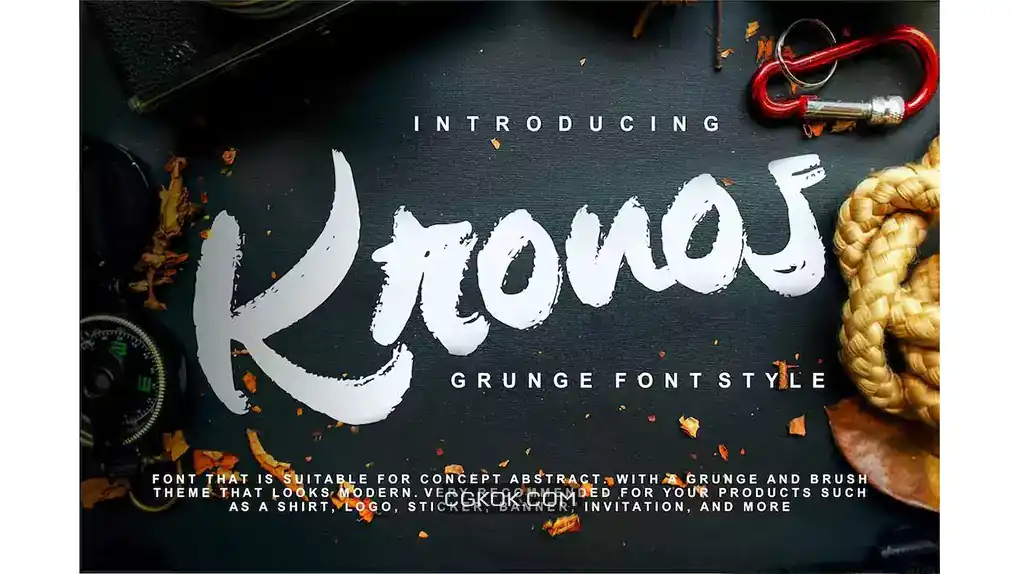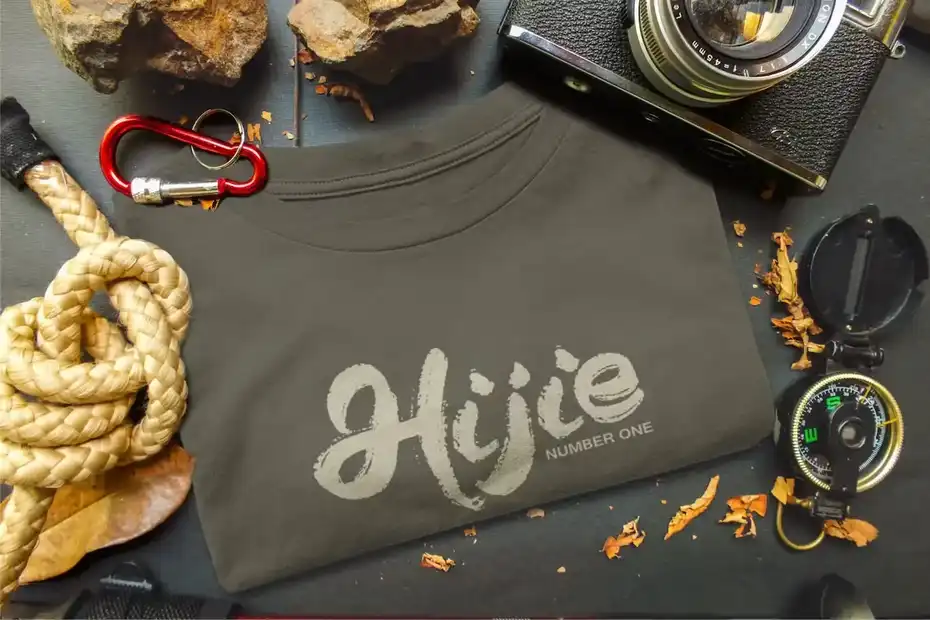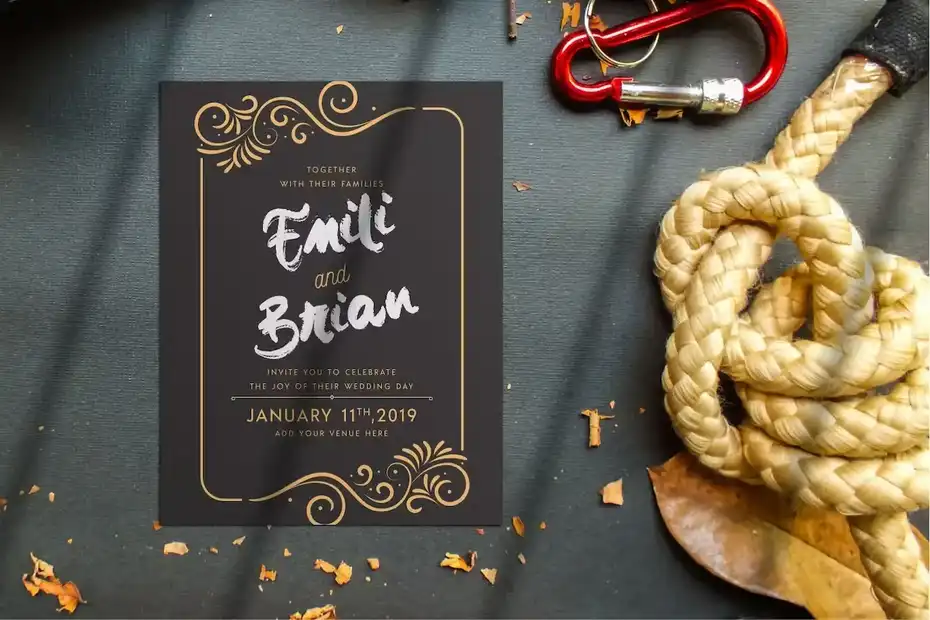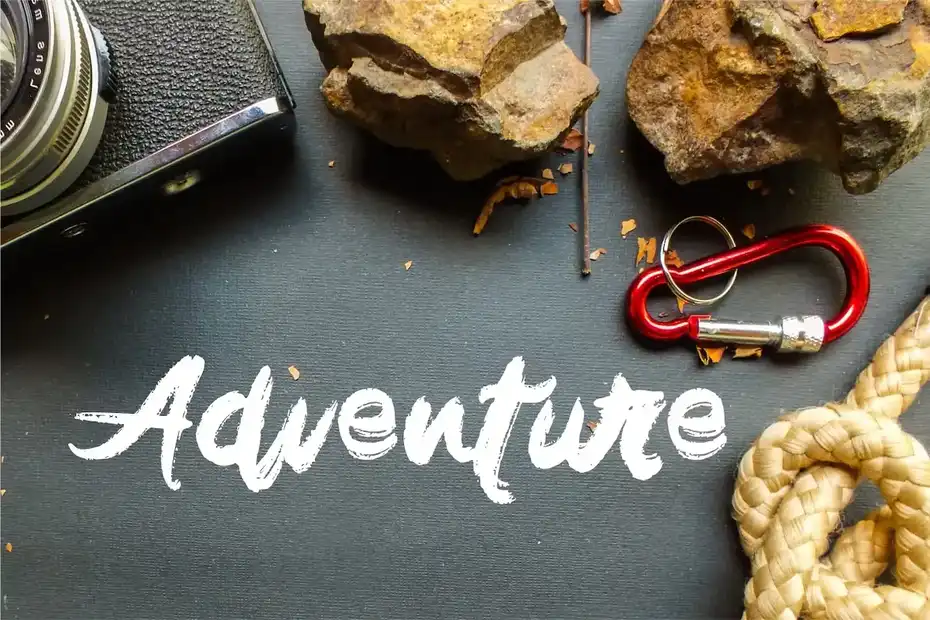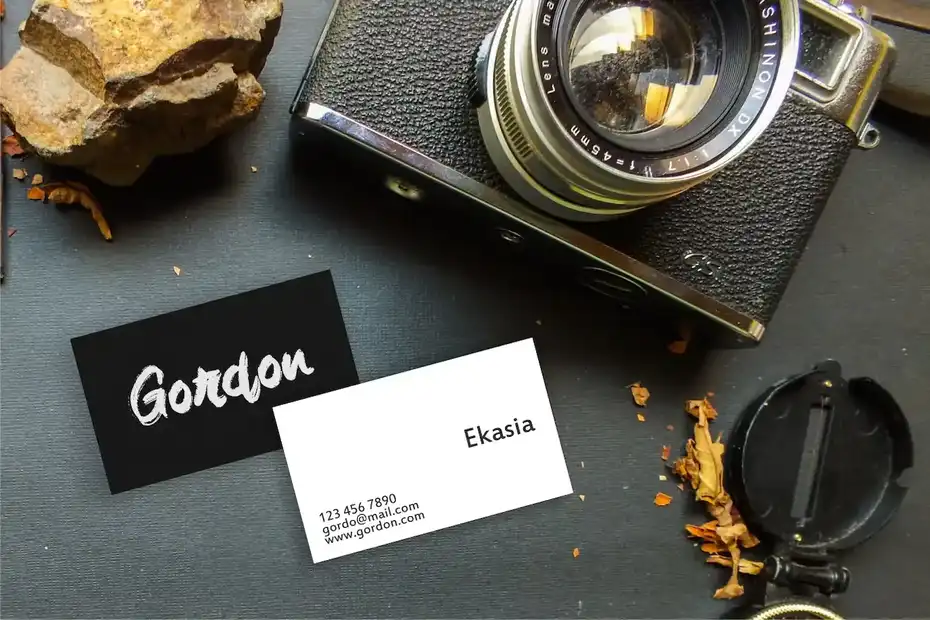
دانلود فونت انگلیسی دست نویس Kronos | Grunge Font Style
فونت انگلیسی دست نویس Kronos | Grunge Font Style : این مجموعه شامل یک فونت انگلیسی دست نویس است که برای لوگو، برندینگ، کارت تبریک، کارت ویزیت، نقل قول، پوستر و غیره مناسب میباشد.
• عنوان مجموعه: Kronos | Grunge Font Style
• فضا بین حروف: معمولی، متراکم، با فاصله